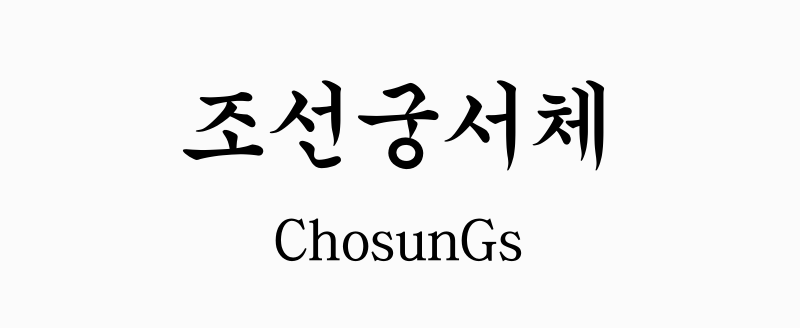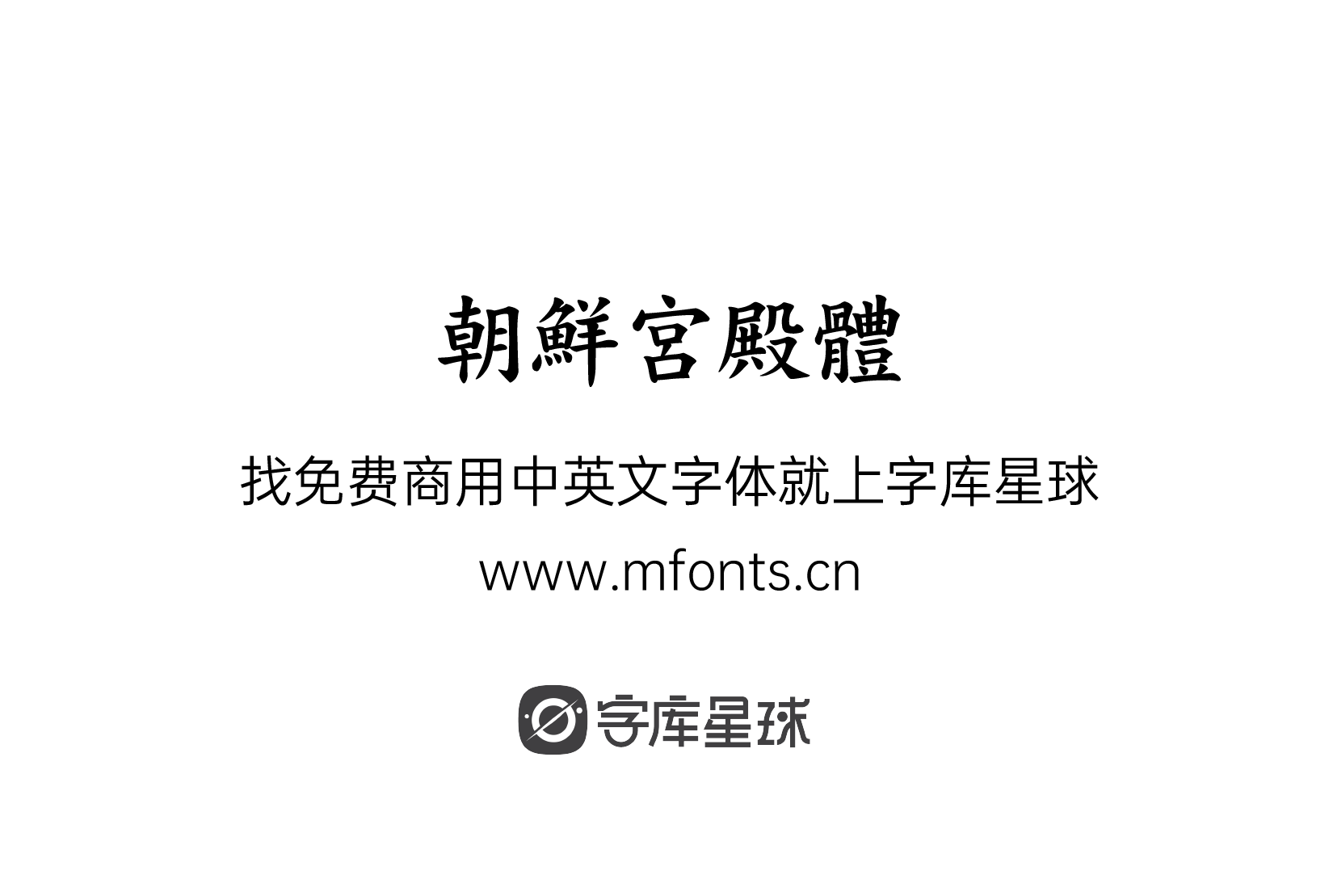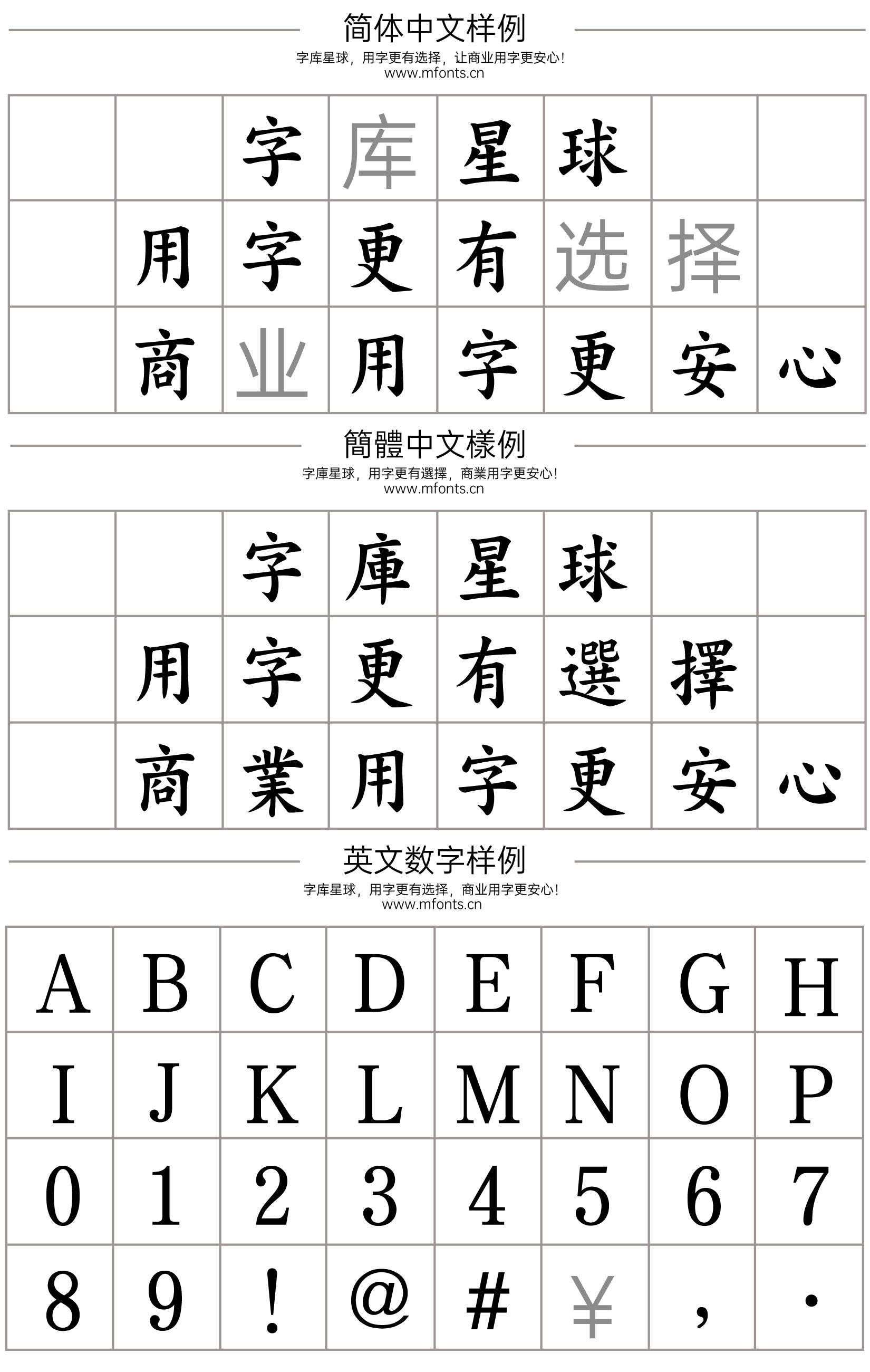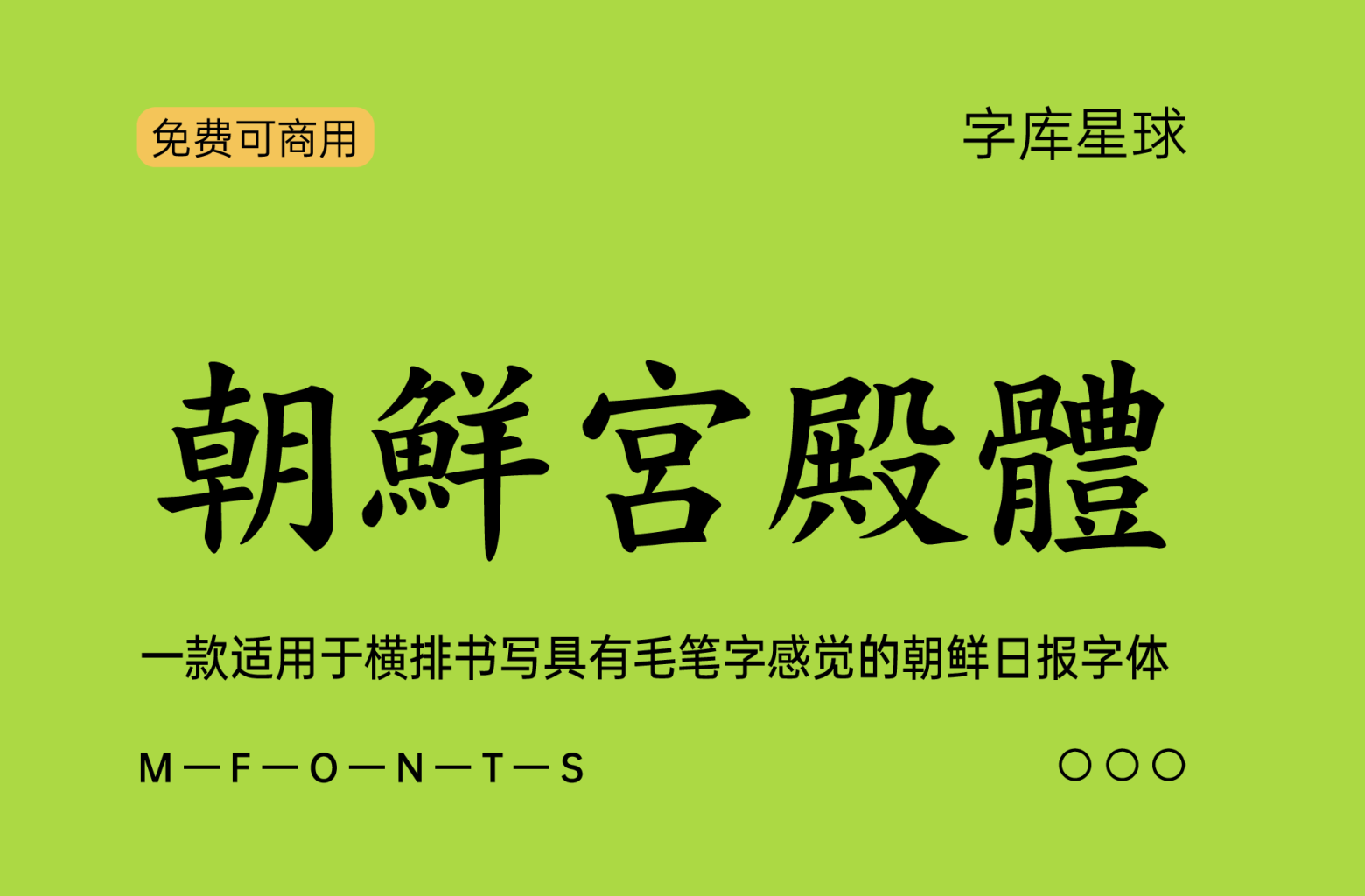
朝鲜宫殿体(조선궁서체)一款适用于横排书写具有毛笔字感觉的朝鲜日报免费可商用字体。
为纪念《朝鲜日报》创刊100周年的《朝鲜100年》我们免费分发“朝鲜100年字体”,这是朝鲜日报在1920年代使用的字体的现代修复版。这种字体由方日荣文化基金会开发,体现了《朝鲜日报》的精神。
为庆祝创刊100周年,我们免费发放《朝鲜日报》独家9种字体。提供了 2007 年发行的“朝鲜日报名作”字体的升级版本。